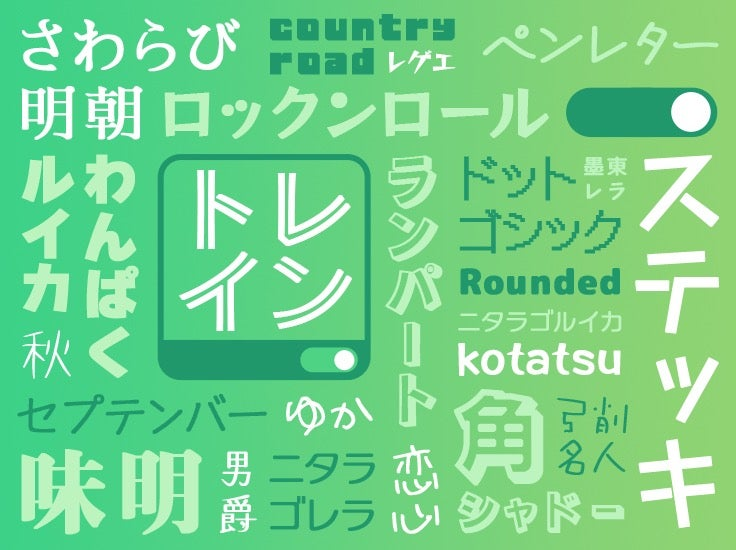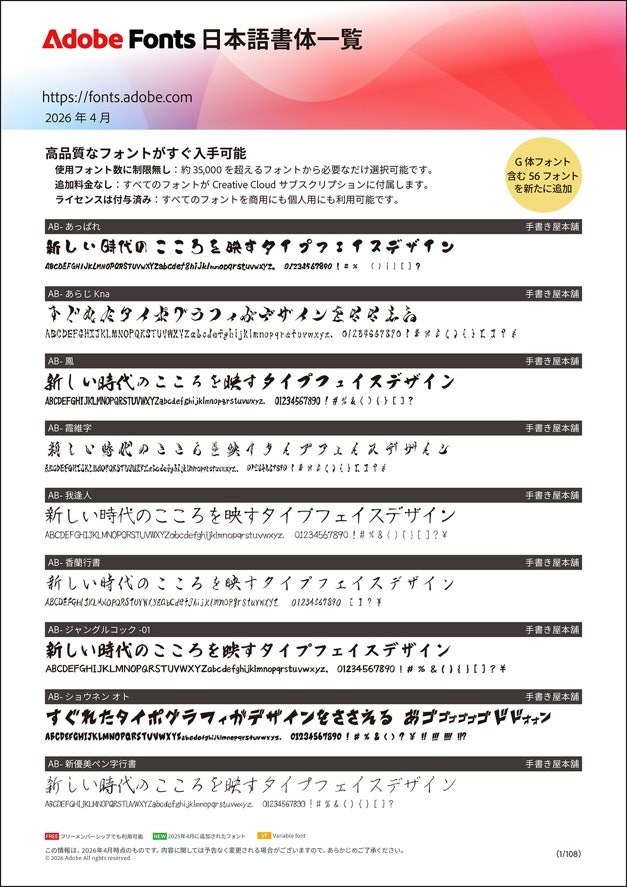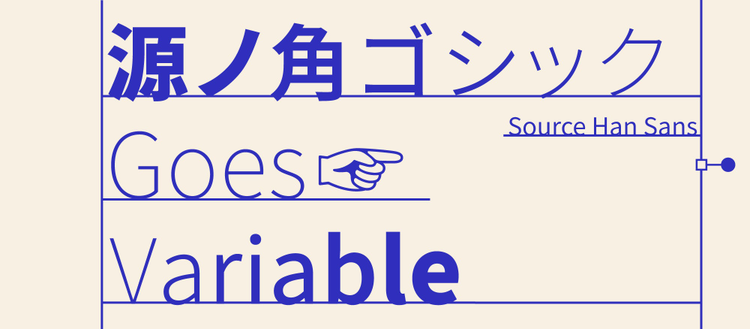
「フォントの日」オンラインイベント開催しました
「こんなに進化しているってフォント!? 〜フォントの⽇だよ全員集合〜」レポート
4月10日「フォントの日」を記念して、フォント業界を盛り上げるべくオンラインイベントを開催しました。
先日ブログにて告知しましたが、4月10日「フォントの日」を記念して、フォント業界を盛り上げるべくオンラインイベントが開催されました。
今回はアドビ岩本と一緒にイベントを盛り上げていただくゲストとして、フォントかるた「2号」伊達千代さん、アニメ研究科の祥太さん、デザイナーのかねこあみさんに参加いただきました。
1つ目のセッションでは、「こんなに進化しているってフォントなんです、判りやすく最新フォント解説」として、アドビのタイムチーム西塚・吉田より、カラーフォントと合成フォントの可能性について、Adobe Fontsに含まれる砧書体制作所「きりこ」を使ったデモや、いまアドビで開発中のカラーフォント「ヒグミン」の紹介を行いました。
フォントのこれからの可能性を感じてワクワクした方も多かったのではないでしょうか。
同じくアドビのタイムチームの服部からは「OpenTypeの基礎知識、知って得するフォントの話」として、異体字の切替え方や、欧文フォントのデザインバリエーションの出し方、文字を組む時に便利な機能などを紹介をしました。知ってるようで知らなかった!?という機能も多くあったのではないでしょうか。
シューレン・ザックリーからは、バリアブルフォント「源ノ角ゴシック」について、バリアブルフォントとは一体どういうものなのか、どんなメリットがあるのかをデモを交えて紹介し、フォントの技術と進化を感じていただけるセッションとなりました。
2つ目のセッション、フォントかるた「2号」伊達千代さんのパートでは、「Adobe Fontsの遊び方、付き合い方」をご紹介いただきました。Adobe Fontsとはどういうものか?どうやって使うのか?という説明に加えて、今回大きく日本語ラインナップが拡充した各ベンダーのフォントの紹介、その中で伊達さんが一推しするフォントを紹介いただだくなど、Adobe Fontsの“味わい方”を紹介いただきました。
3つ目の各フォントベンダーからのセッションでは、各社から発表されるいま注目のフォントや近日リリース予定の新書体紹介、各社の製品紹介など多くのトピックが詰まった時間となりました。
見応えたっぷりに大盛況となったフォントの日オンラインイベント。
当イベントでもご案内させていただきましたが、今回Adobe Fontsは大きくアップデートをしました。日本語のフォントラインナップが強化され、種類も430を超えてますますお使いいただきやすくなりました。